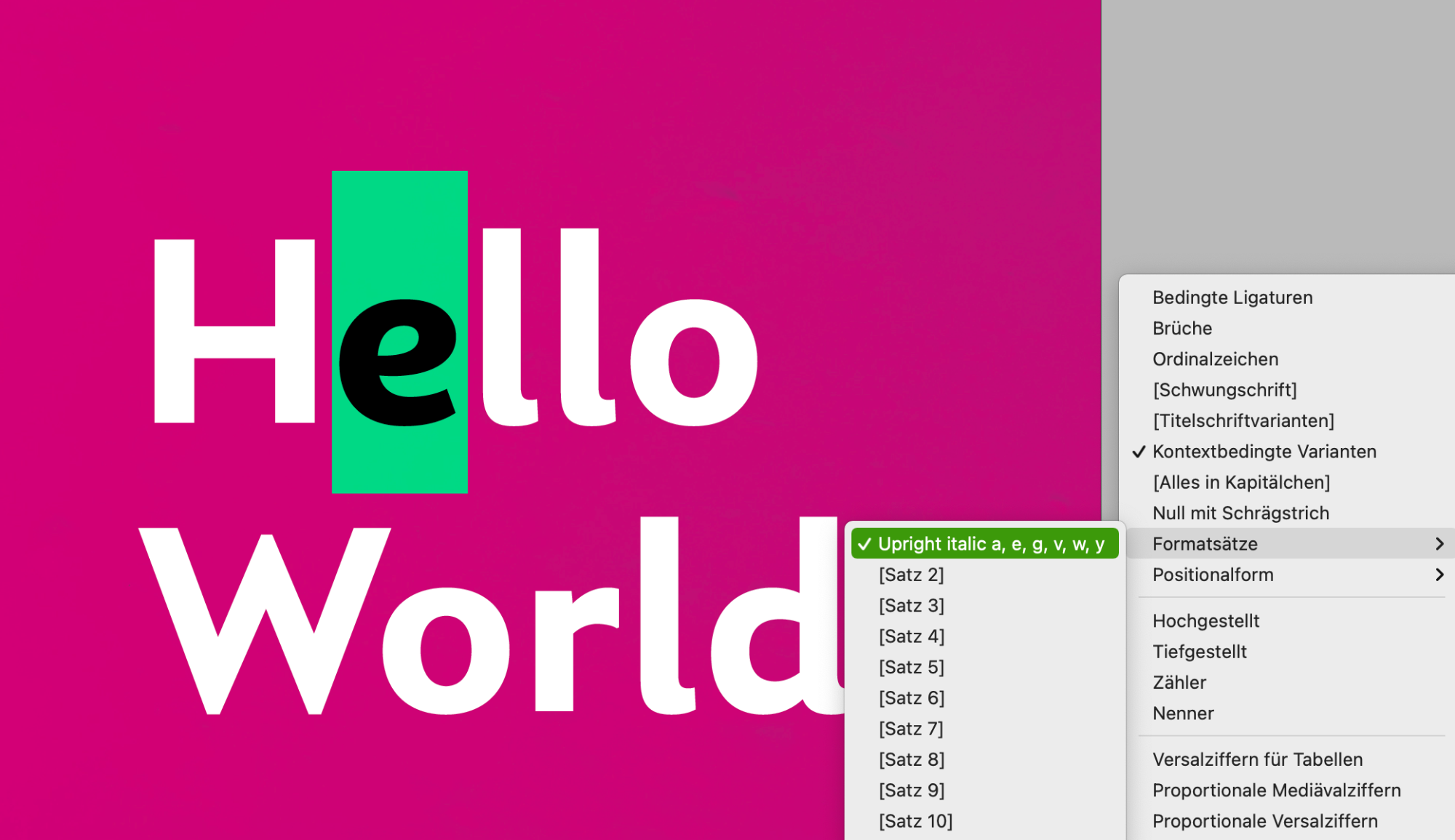
für ein Projekt suche ich momentan nach Schriften mit Buchstabenformen, die in den Bereich der Upright Italics fallen (z. B. Adria Grotesk). Im Speziellen geht es mir um das runde e, wie man es aus kursiven Schriften kennt – nur eben aufrecht. Es sollte sich um eine Groteskschrift mit wenig Strichstärkenkontrast handeln; das gemeine e darf auch gern in einem Stylistic Set enthalten sein. Vielleicht hat ja jemand eine passende Schrift vor Augen.
Genau, danke. Die Bree hatte ich auch schon beim Wickel – die ist mir allerdings etwas zu humanistisch. Ich habe die Hoffnung, dass es auch nüchtern-geometrische Groteskschriften mit einem solchen e gibt.
nüchtern-geometrische Groteskschriften
Ui, das wird schwieriger. Da ploppt spontan gar nichts bei mir auf. Ich werde mal durch die Fonts scrollen.
@Dieter Stockert Bei der Labrador, der Libertad und der Mato Sans finde ich in den aufrechten Schnitten kein Upright-Italic-e. Ist das in stylistischen Sets versteckt? In den Glyphenübersichten konnte ich nichts entdecken. Entgeht mir da irgendwas? Bin ich e-blind?
Für meine Zwecke passend erscheinen mir die Rebrand, Metro Nova, Agile und Ping. Über letztere bin ich gestern auch noch gestolpert. Da ihr Formenprinzip mit den tropfenartigen Punzen ganz hervorragend zu meinem Projekt passen, ist das tatsächlich ein aboluter Glückstreffer.
Agile
Die Agile hab ich zufällig da – ich kenne den Schriftgestalter über zwei Ecken und hab Sie von ihm zum testen. Ich kann dir bei Bedarf gern etwas Text absetzen ...
Bei der Labrador, der Libertad und der Mato Sans finde ich in den aufrechten Schnitten kein Upright-Italic-e.
Nachdem ich jetzt zu einer zivileren Uhrzeit und nicht abgelenkt durch die Green Bay Packers noch mal hinschaue, muss ich Dir Recht geben.